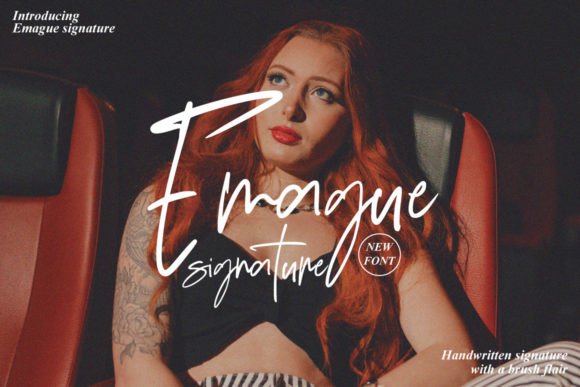
Emague
Emague – A Fonte que Transforma Ideias em Escrita Elegante
Se você busca uma fonte que una sofisticação e personalidade, Emague chega como a escolha perfeita. Desenvolvida com traços orgânicos e fluídos, ela traz à tona a sensação de uma escrita manual autêntica, ideal para projetos de branding, convites, posts de redes sociais e qualquer peça que precise de um toque humano.
- Design orgânico: Cada letra foi cuidadosamente modelada para garantir um fluxo natural, como se fosse escrita à mão.
- Versatilidade criativa: Perfeita para identidade visual, convites de casamento, cartões de visita, capas de e‑books e conteúdo digital.
- Glyphs e ligaduras avançadas: Por ser PUA encoded, oferece acesso fácil a um extenso conjunto de glifos e ligaduras que enriquecem ainda mais o layout.
- Calor e autenticidade: Transmite sensação de proximidade e confiança, conectando o público ao seu conteúdo de forma emocional.
Por que escolher Emague?
Em projetos de branding, a tipografia é tão importante quanto o logotipo. Emague cria uma identidade que parece escrita à mão, mas com a qualidade e a consistência de uma fonte profissional. Isso faz com que sua marca se destaque nas timelines do Instagram, nos e‑mails de marketing e nas embalagens de produtos.
Aplicações Ideais
- Convites de casamento e festas
- Cartões de visita e papelaria corporativa
- Postagens e stories de redes sociais
- Capa de livros, e‑books e revistas digitais
- Identidade visual de marcas artesanais e boutique
Emague não é apenas mais uma fonte; é uma ferramenta de storytelling visual que adiciona calor e autenticidade a qualquer projeto. Se você deseja que sua comunicação escrita se destaque e crie conexão emocional com o público, esta fonte será, sem dúvidas, um dos seus maiores aliados.